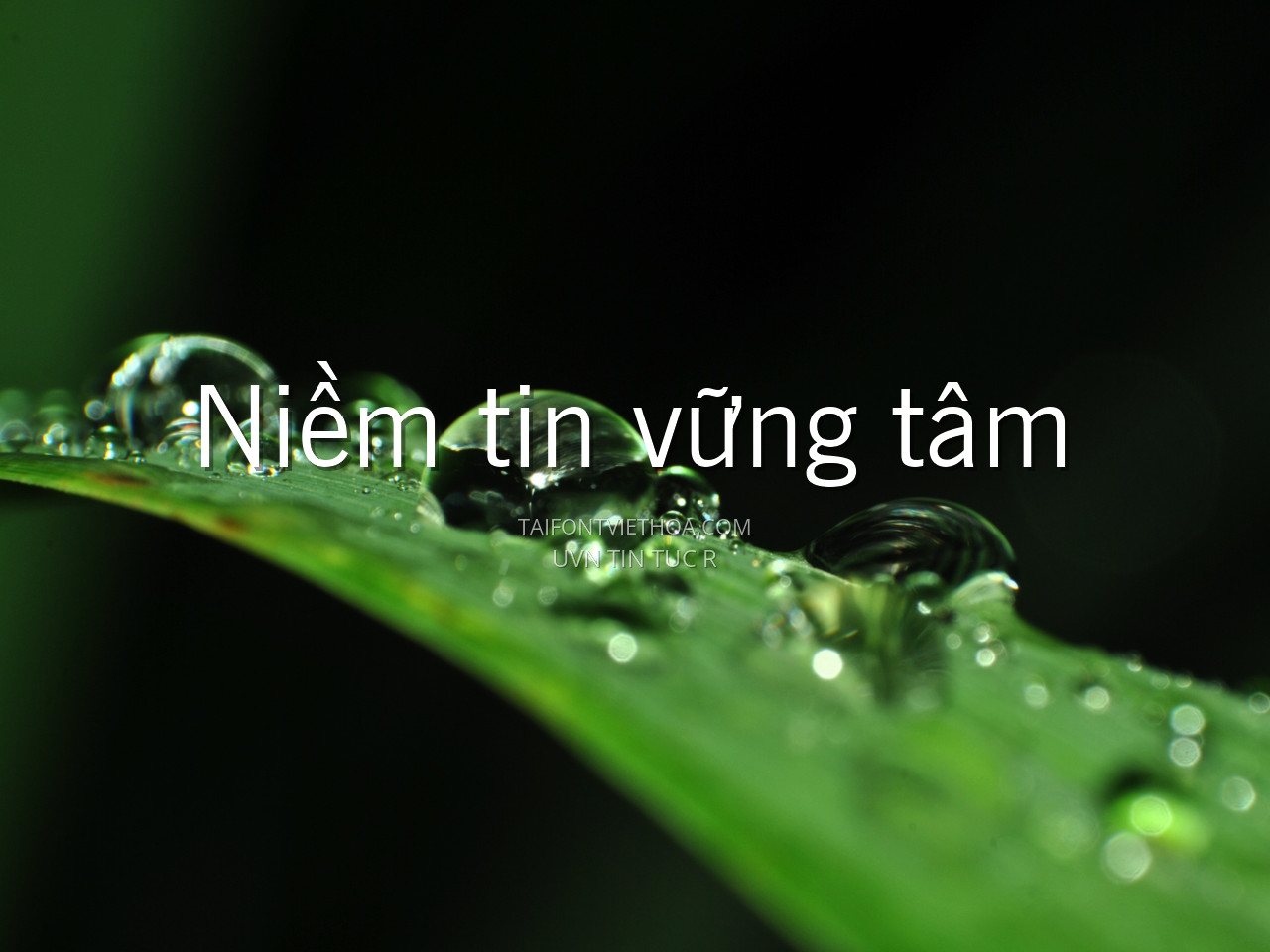
Font việt hóa UVN Tin Tuc
Giới thiệu về font UVN Tin Tuc
UVN Tin Tuc là một kiểu chữ được thiết kế với mục tiêu truyền tải thông tin một cách nhanh chóng, rõ ràng và dễ tiếp cận, rất phù hợp với các nội dung báo chí, truyền thông và tin tức số. Với hình thức hiện đại và độ dễ đọc cao, font UVN Tin Tuc được sử dụng phổ biến trong các sản phẩm truyền thông đại chúng như tiêu đề bài báo, nội dung tin tức, hay các thiết kế liên quan đến thời sự – truyền hình. Font đã được sưu tầm và chia sẻ bởi thành viên Font Chuẩn, và hiện nay được taifontviethoa.com chọn lọc, sử dụng trong các dự án thực tế nhằm phục vụ nhu cầu truyền thông hiện đại và tối ưu khả năng hiển thị chữ Việt.
Đặc điểm thiết kế và ứng dụng của UVN Tin Tuc
Font UVN Tin Tuc thuộc nhóm sans-serif hiện đại với các đường nét thẳng, đều và dứt khoát. Cấu trúc chữ rõ ràng, các ký tự có độ cao hợp lý giúp tối ưu khả năng đọc lướt – một yêu cầu quan trọng trong ngành báo chí và truyền thông. Font hỗ trợ đầy đủ tiếng Việt, đảm bảo tính nhất quán khi trình bày trên mọi nền tảng từ in ấn đến kỹ thuật số.
Ứng dụng lý tưởng: tiêu đề bản tin, bài viết báo chí, slide thuyết trình, thiết kế banner truyền hình, trang báo mạng. Ngành nghề phù hợp: truyền thông, báo chí, công nghệ, marketing số, thiết kế nội dung tin tức đa nền tảng.